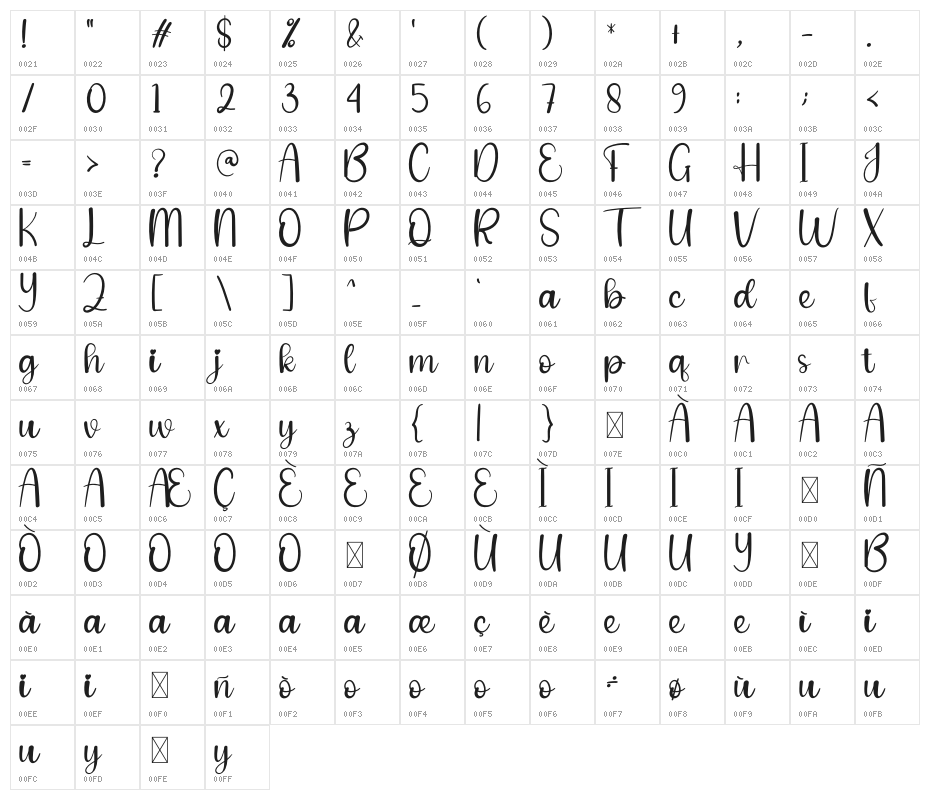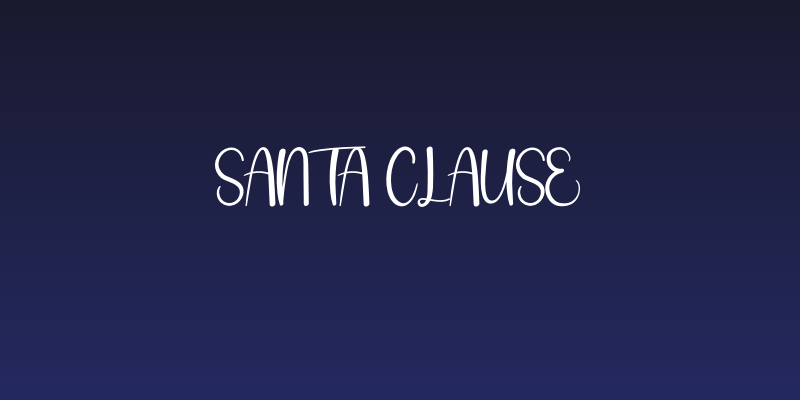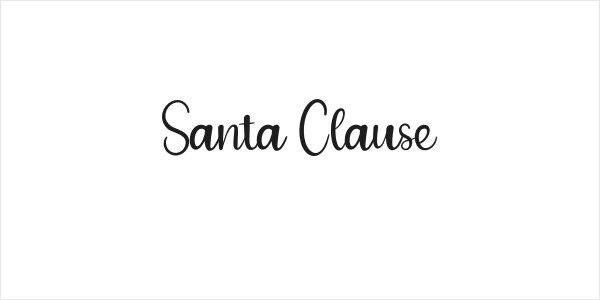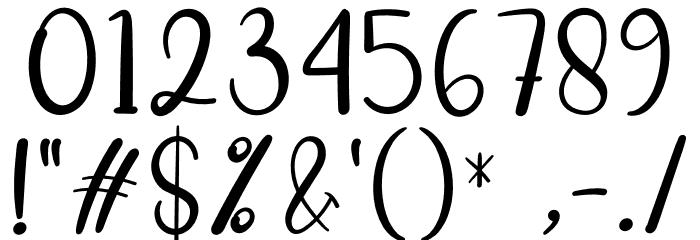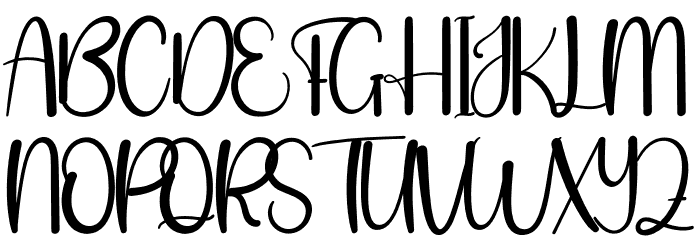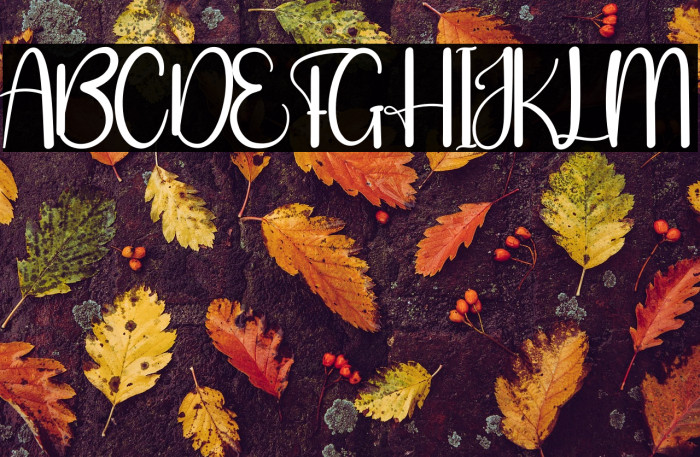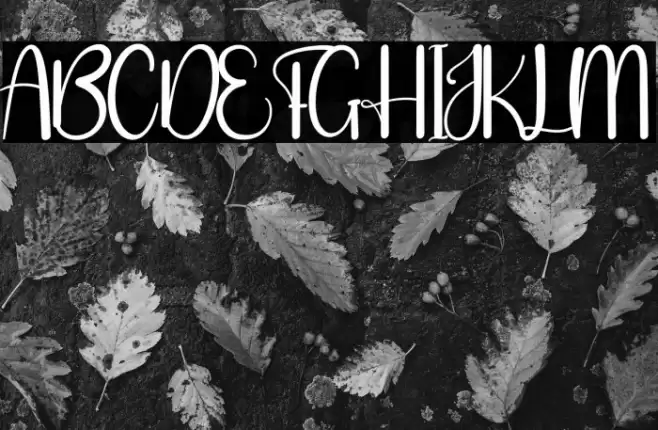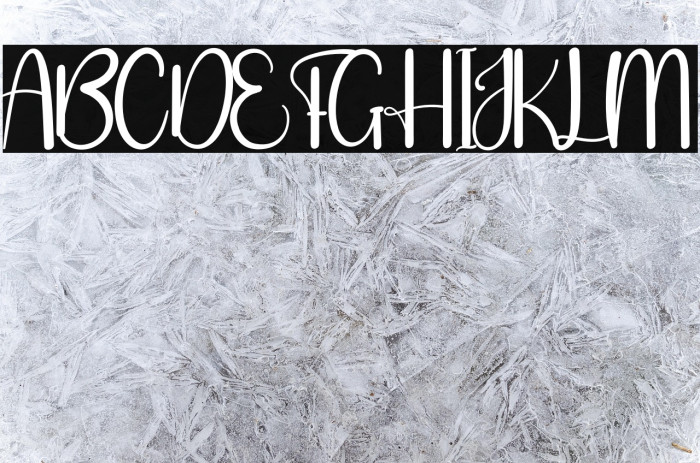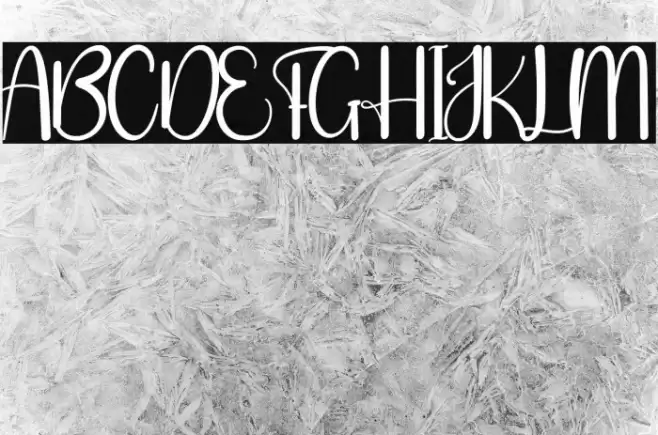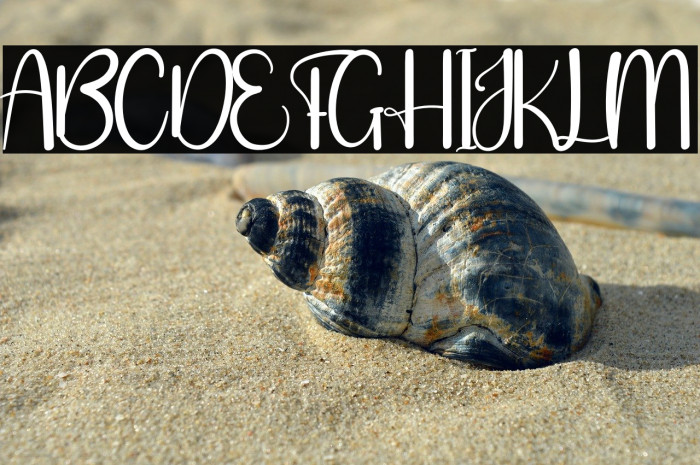
Santa Clause Font
| Anwendungsfall | Logos, Invitations, Greeting Cards |
| Vorgeschlagene Projekte | Ideal for greeting cards, invitations, branding projects, and any design requiring a touch of elegance and playfulness. |